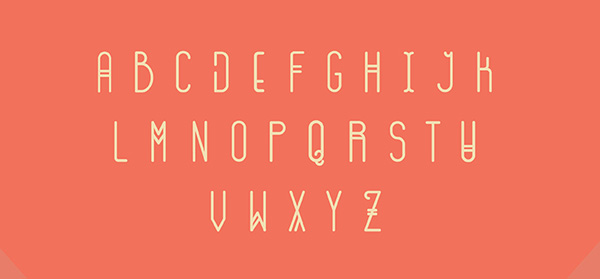
3 tipografías sin serifa GRATIS
Os dejo para terminar la semana estas tres tipografías paloseco gratuitas que os pueden resultar muy útiles para cabeceras y pequeños bloques de texto. La licencia es libre así que podéis utilizarla tanto para proyectos personales como comerciales. Para descargarlo pulsad sobre la imagen o en el link del pie de la entrada. Espero que os sirva y recordad que los like y los follow ayudan mucho así que visitadnos en Twitter y Facebook. También nos podéis encontrar en Flipboard buscando nuestra revista El Arquitecto de Ilusiones.
Anabella, tipografía caligráfica GRATIS
Para acabar la semana os dejo una tipografía de estilo caligrafía para que os descarguéis totalmente gratis. La licencia es libre así que podéis utilizarla tanto para proyectos personales como comerciales. Para descargarlo pulsad sobre la imagen o en el link del pie de la entrada. Espero que os sirva y recordad que los like y los follow ayudan mucho así que visitadnos en Twitter y Facebook. También nos podéis encontrar en Flipboard buscando nuestra revista El Arquitecto de Ilusiones.
Exodus, tipografía GRATIS
Seguimos con Enero y por fin empieza a hacer frío. Os dejo una tipografía decorativa muy útil para cabeceras o diseños similares. La licencia es libre así que podéis utilizarla tanto para proyectos personales como comerciales. Para descargarlo pulsad sobre la imagen o en el link del pie de la entrada. Espero que os sirva y recordad que los like y los follow ayudan mucho así que visitadnos en Twitter y Facebook. También nos podéis encontrar en Flipboard buscando nuestra revista El Arquitecto de Ilusiones.
Gogoia, tipografía GRATIS
Os dejo una tipografía gratuita para encarar este fin de año. La licencia es libre así que podéis utilizarla tanto para proyectos personales como comerciales. Para descargarlo pulsad sobre la imagen o en el link del pie de la entrada. Espero que os sirva y recordad que los like y los follow ayudan mucho así que visitadnos en Twitter y Facebook. También nos podéis encontrar en Flipboard buscando nuestra revista El Arquitecto de Ilusiones.